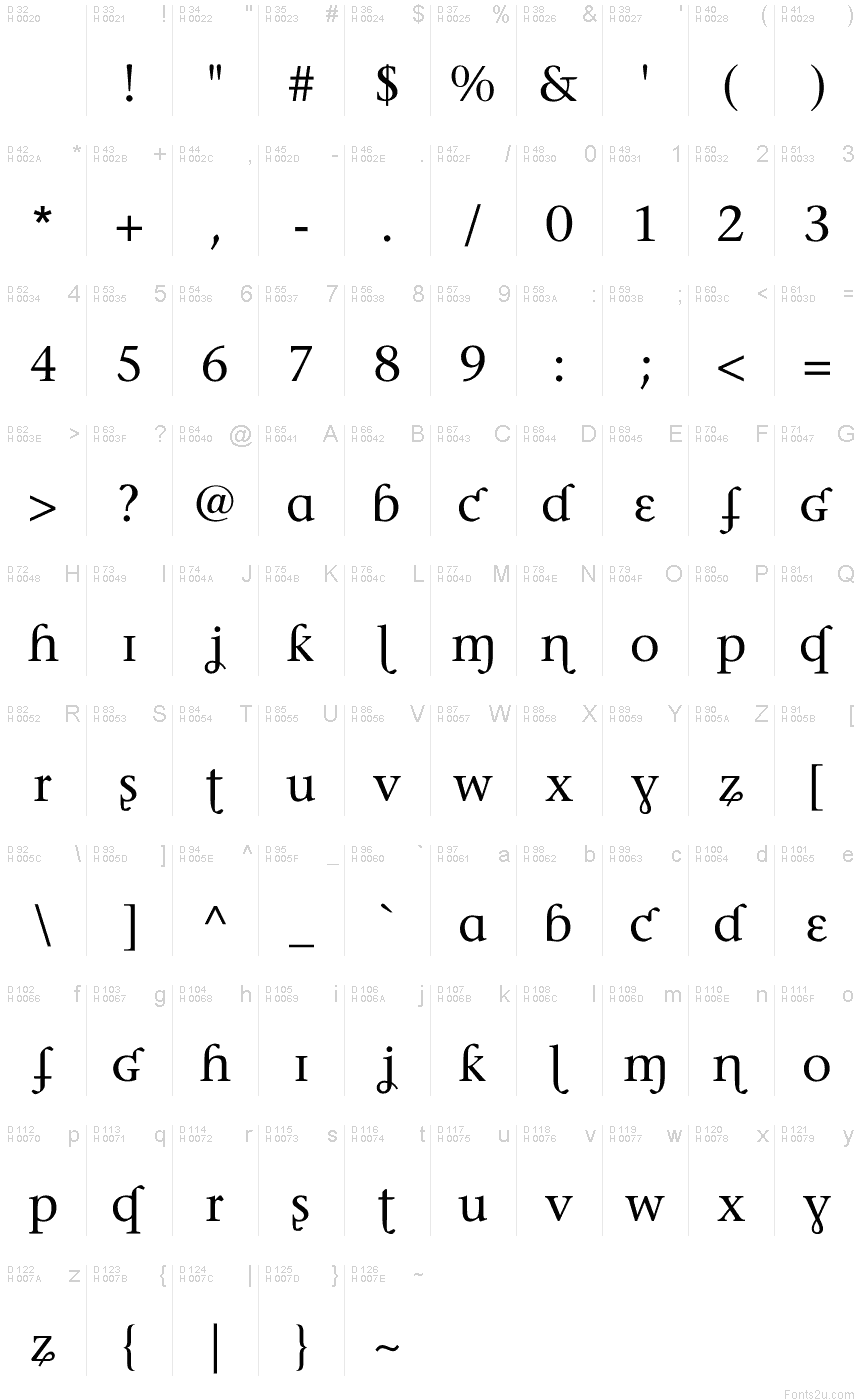
Phonetica
Phonetica od Dasklem Inc. to darmowy szeryfowy font typu display o literackim, lekko wyrafinowanym charakterze. Litery łączą klasyczny kontrast znany z książek z nieoczekiwanymi zawijasami i haczykami, dzięki czemu całość plasuje się gdzieś pomiędzy formalnym składem redakcyjnym a wyrazistym, osobowym krojem szeryfowym.
To sprawia, że jest naturalnym wyborem do winet magazynów, tytułów albumów, napisów na plakatach, butikowych opakowań i krótkich tekstów na okładkach książek, gdzie darmowy font ma wnieść trochę kulturalnego dramatu, nie stając się przy tym przesadnie zdobnym. Sprawdza się również w monogramach czy identyfikacji wizualnej opartej na inicjałach, ponieważ zwężane kreski i pętelki nadają nawet krótkim słowom wyrazistą sylwetkę.